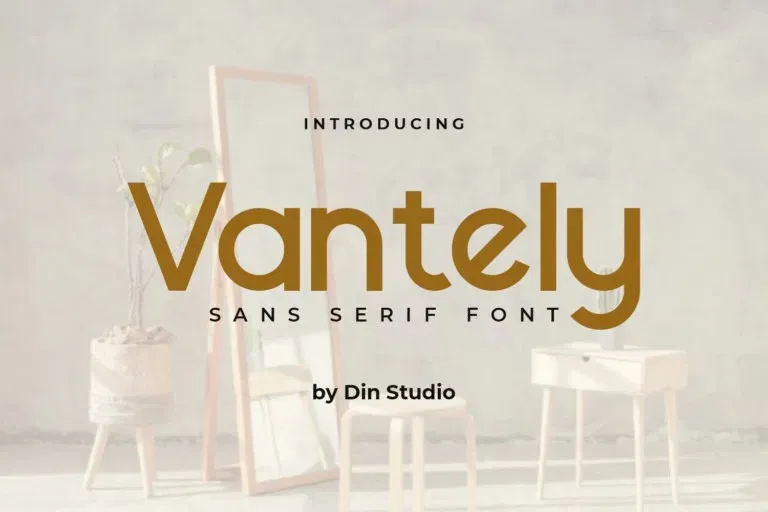
A Vantely Font é uma escolha ótima para projetos profissionais e de marca que buscam estilização atraente com simplicidade. Criada pela Din Studio, essa fonte geométrica sem serif apresenta caracteres redondos e finos, perfeita tanto para impressão quanto para branding. Seu design elegante é adequado para qualquer projeto que exige uma aparência moderna e moderna. Com cada letra ganhando um toque único e belo, a Vantely Font é especialmente indicada para trabalhos de marketing onde você deseja destacar frases ou citações com estilo. Suas linhas retas e claras garantem que a fonte seja fácil de ler em grande escala, tornando-a uma escolha versátil tanto para negócios quanto para o design editorial.